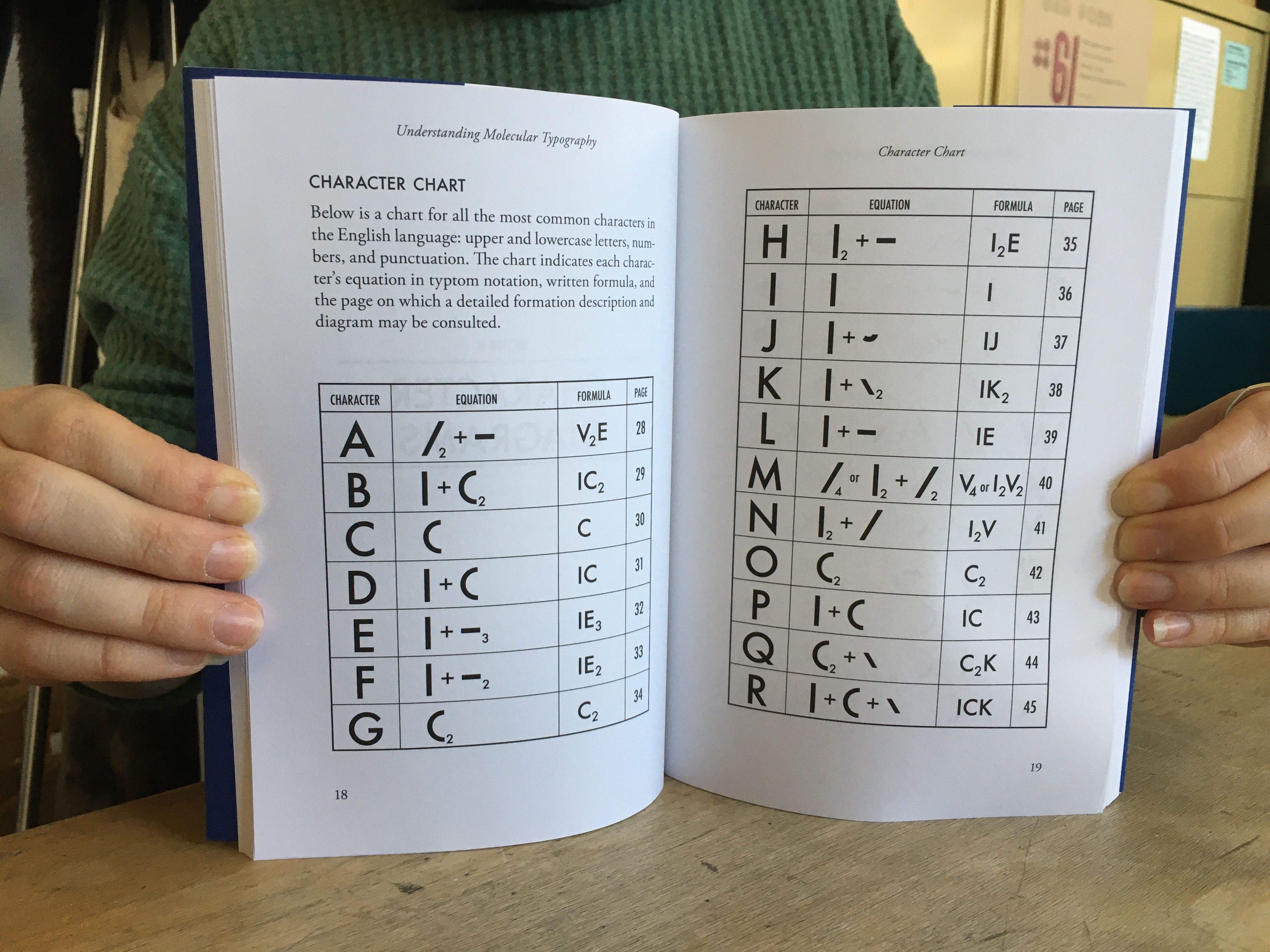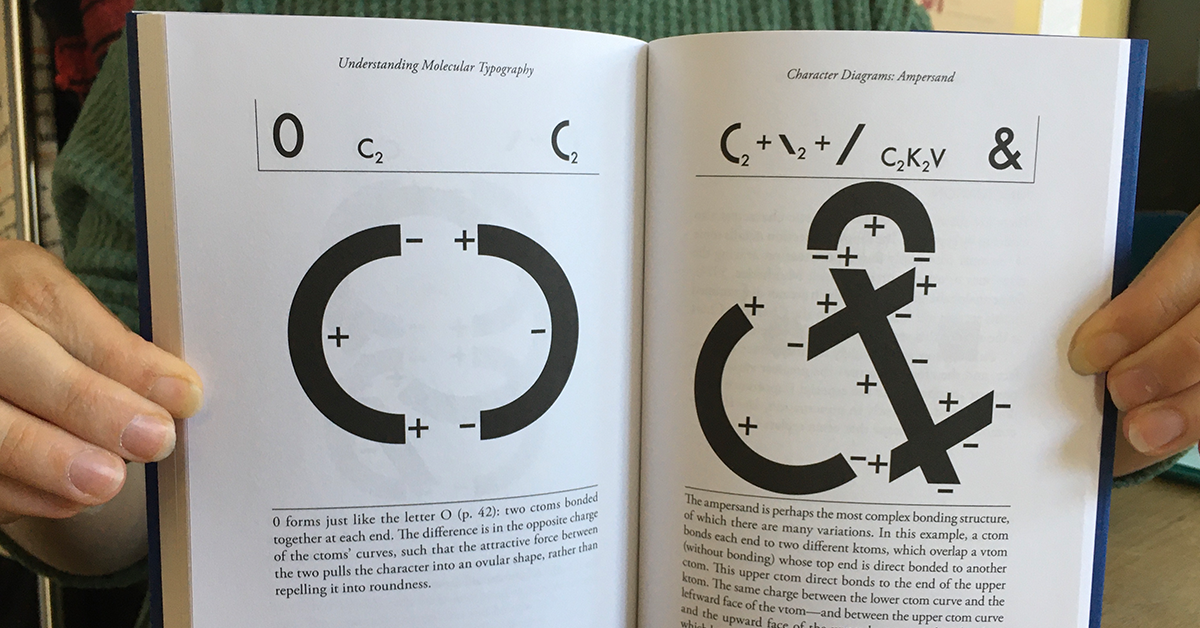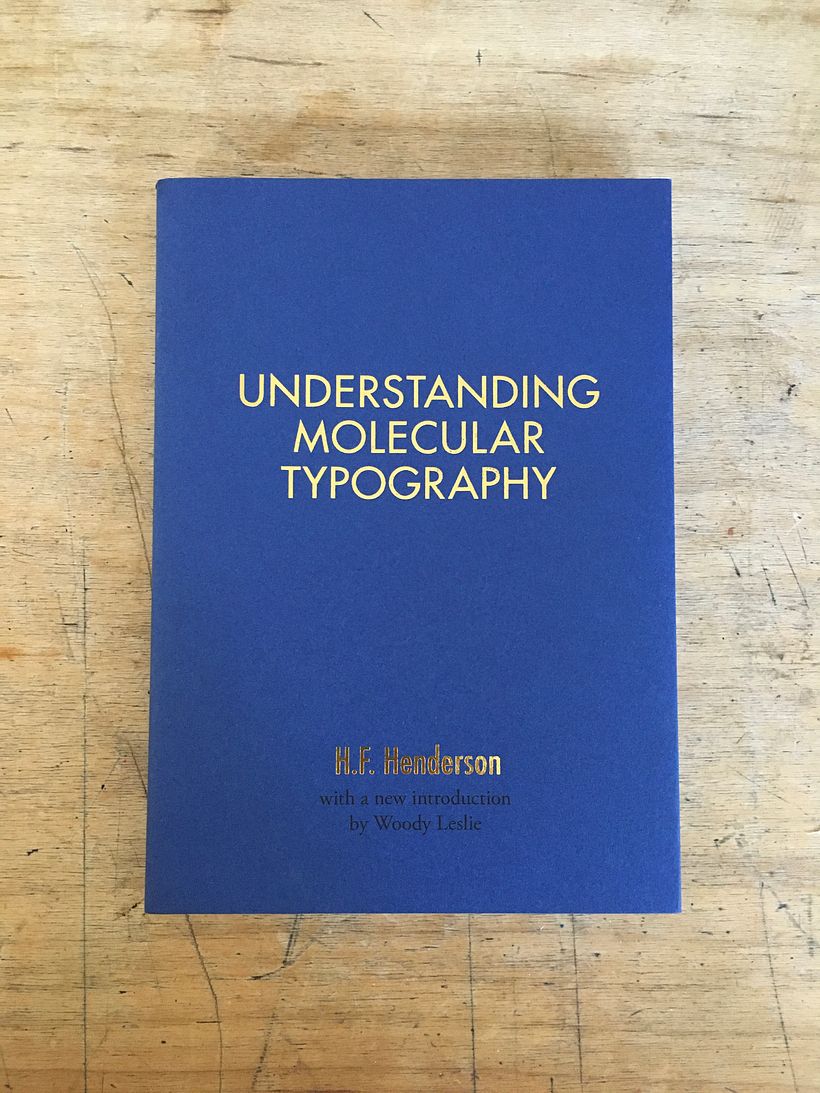
¿Qué es la tipografía molecular?
Conoce una visión inesperada sobre las letras, que las considera como seres vivos
La tipografía molecular es el estudio de las letras, que se consideran moléculas, y tienen ciertas propiedades físicas y químicas. Todos los caracteres se forman a partir de siete bloques atómicos básicos llamados tiptomas (typtoms). Cuando se combinan los tiptomas, se forman las letras, los números y la puntuación, tal y como sucedería en la química, cuando los elementos forman moléculas complejas.
La letra está viva
La tipografía molecular, según sus defensores, no es una teoría, ni una metáfora o una herramienta de análisis tipográfico, sino que las letras se estudian como entes orgánicos. Por ejemplo, los tiptomas tienen polos positivos y negativos que se atraen y repelen para dar vida a la forma final. Estos principios funcionan en distintos tipos de fuentes y estilos tipográficos, en mayúsculas y minúsculas, así como en alfabetos no latinos.
Cada letra, número y signo de puntuación tiene una ecuación y una fórmula “química” que indica la estructura de sus tiptomas, como se ve en este diagrama de la letra H.
Inspiración científica
Esta aproximación a la tipografía que propuso que las letras son como organismos vivos, surgió en la década de los cincuenta, por el trabajo de Aaron Edwards y Charles Harrington. Ellos plantearon la tipografía molecular como un hecho científico: afirmaron que la letra impresa está hecha de moléculas reales, y al ser un objeto físico y real, tiene estructuras químicas y físicas particulares.
En este ejemplo, la letra A se forma de los tiptomas vtoms y etom. Se aprecia cómo las cargas eléctricas de las caras de la letra se atraen (positivo atrae negativo) o se repelen, lo que provoca la orientación propia de la letra.
Rescate de la teoría
En los años noventa, H. F. Henderson compiló en su libro Understanding Molecular Typography los hallazgos de la tipografía molecular. El libro se convirtió en un éxito que por primera vez hizo la teoría digerible para el público no experto.
Después de que se dejara de imprimir, en 2019 la editorial Ugly Duckling Presse lo reeditó con el delicado trabajo de análisis del encuadernador Woody Leslie, una verdadera autoridad en tipografía molecular. ¿El objetivo? Rescatar el peculiar trabajo de Henderson, al menos con el propósito de “demostrar las frecuentes ideas erróneas en la ciencia que ha tenido la humanidad a lo largo de la historia”.
Woody Leslie habla de cómo este libro lo tomó por sorpresa cuando lo conoció, y algo similar le ocurrirá a todos los amantes de la tipografía y de las letras. El libro es una fuente de inspiración, un enfoque por demás meticuloso a la esencia de la letra. Gracias a su estudio, la tipografía molecular está recibiendo un renovado interés entre los tipógrafos y amantes de las letras en general.
El libro contiene estudios detallados de los caracteres latinos, y resulta fascinante analizar sus principios. En este ejemplo vemos al ampersand, "quizá la estructura más compleja de enlaces". Las cargas de los tiptomas que se atraen y repelen dan el giro peculiar de la letra y permite que algunos se superpongan sin estar enlazados.